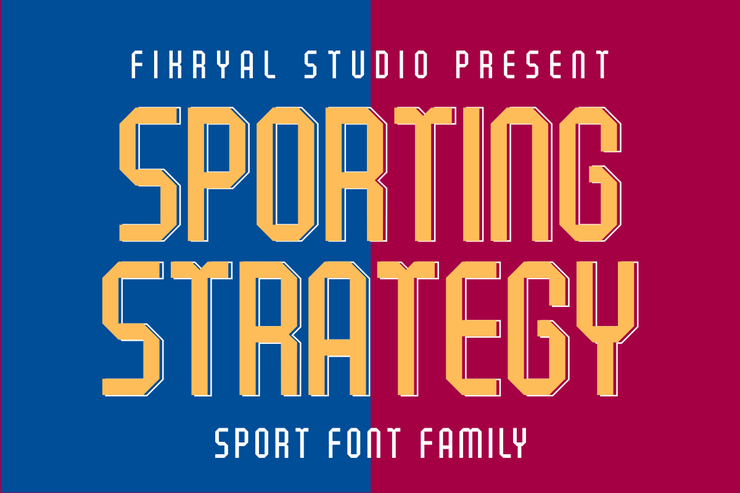
Sportstrategie Moderne kühne Sport-Stil englische dekorative Schrift
Sporting Strategy ist eine kraftvolle, sportlich inspirierte, dekorative englische Schrift mit kräftigen Strichen, scharfen Winkeln und dynamischen geometrischen Strukturen. Sie vermittelt Energie, Wettbewerbsfähigkeit und moderne Vitalität und passt perfekt zu Sportereignissen, Fitnessmarken und sportbezogenen visuellen Kreationen. Diese stilvolle Schrift wird häufig für Sportmannschaftslogos, Fitnessposter, Veranstaltungsbanner, den Druck von Sportbekleidung, Sportinhalte in sozialen Medien und sportliches Verpackungsdesign verwendet. Komplett mit Groß- und Kleinbuchstaben ist sie hochgradig skalierbar und lässt sich leicht in Farben, Größen und Layouts anpassen, wobei ihre starke sportliche Textur erhalten bleibt. Geeignet für Grafikdesigner, Sportorganisationen und kommerzielle Branding-Projekte, um auffällige, energiegeladene visuelle works.Free für den gewerblichen Gebrauch zu schaffen / Kein Copyright 1